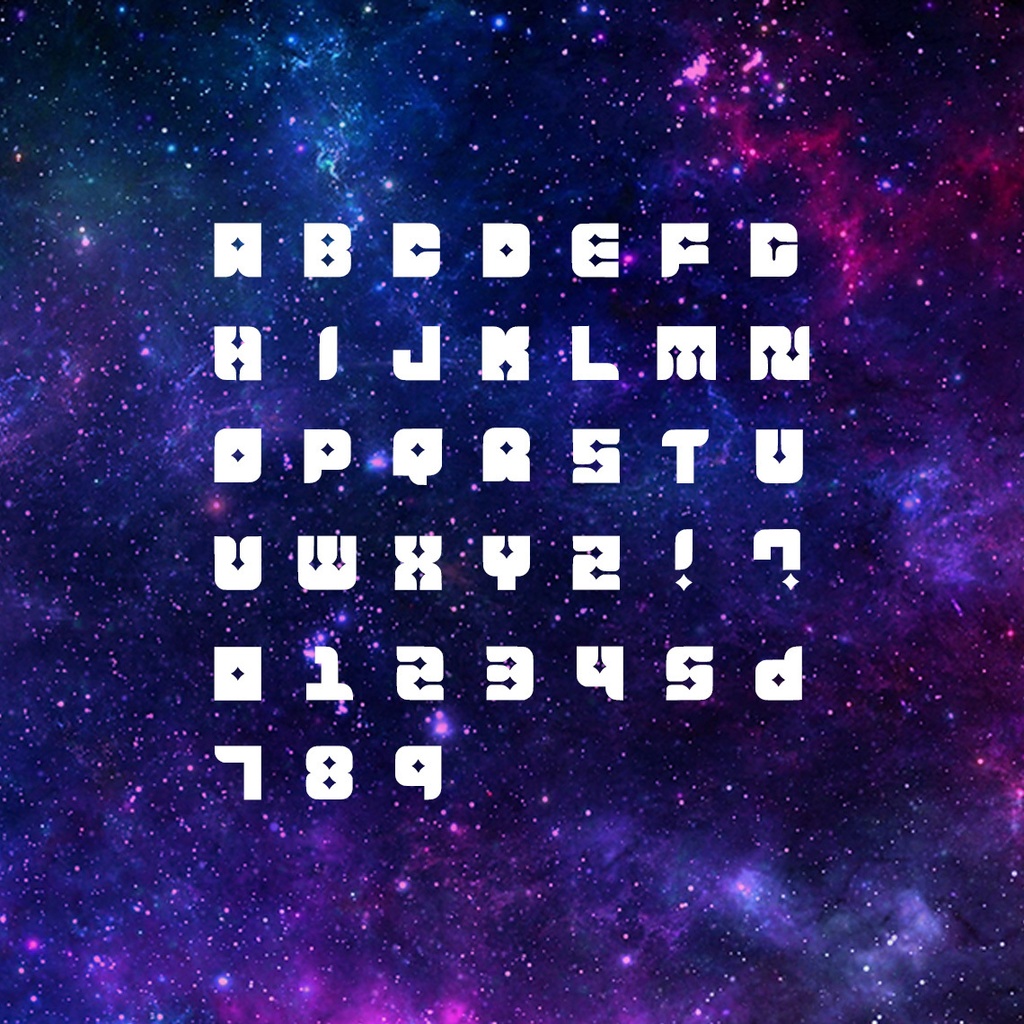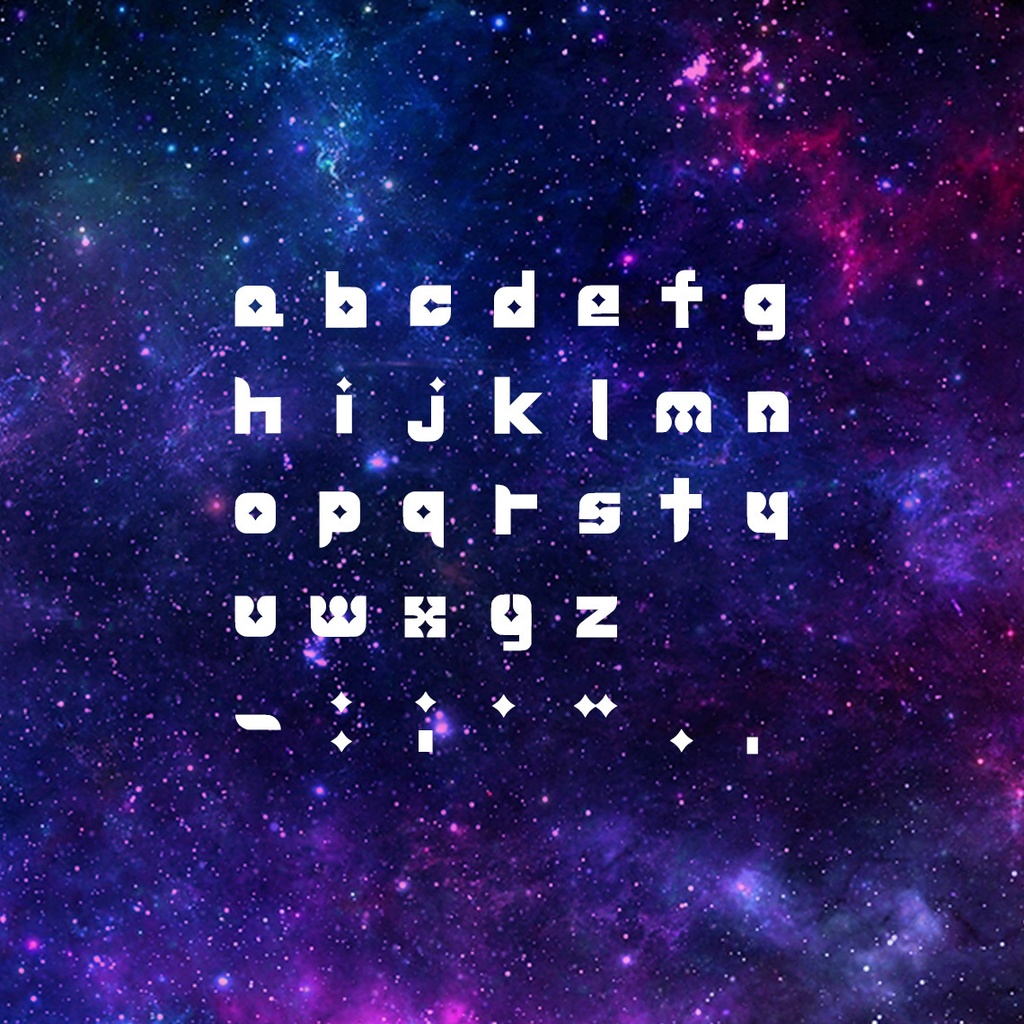
【無料】Square Invader (すくえあいんべーだー)【フリーフォント】
宇宙から来たかわいい侵略者のフォントです! ぱっと見は文字っぽくないけどよく見ると読めるデザインフォントです サイバー・SF系のあしらいに使いたくて作りました 自分用に作ったのでまだ調整が甘いところがあります… 使いどころがあるか分からないですがよければ使ってみて下さい ●フォント名 Square Invader ●収録文字 ABCDEFGHIJKLMNOPQRSTUVWXYZ0123456789!?.,:;'" abcdefghijklmnopqrstuvwxyz ●利用規約 ◎商用利用可能(ロゴなどへの使用可) ◎著作表記不要 ×自作発言、AI学習への利用、フォントファイルの再配布、フォントを利用した素材の配布 https://ramune-material.com/terms/ ※ソフトウェアへの埋め込みは要相談 個別の事例についてご不明点がございましたらメール又はXのDMよりご連絡ください ================================= 2025/04/10 V3.0配布(小文字&記号対応) 2024/02/03 V1.0配布 作った人:清涼院ラムネ [mail] seiryoin.ramune@gmail.com [X] https://twitter.com/seiryoin_ramune [YouTube] https://www.youtube.com/@seiryoin_ramune =================================